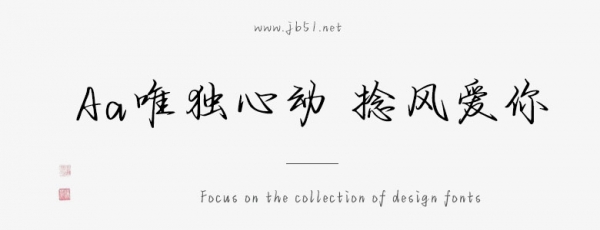
Aa唯獨(dú)心動(dòng) 捻風(fēng)愛你由Aa字庫出品的藝術(shù)字體,字體筆觸纖細(xì),書寫流暢,適合應(yīng)用于藝術(shù)設(shè)計(jì)、平面宣傳設(shè)計(jì)、網(wǎng)頁設(shè)計(jì),書法字帖等領(lǐng)域。有需要的朋友快來本站下載使用吧。